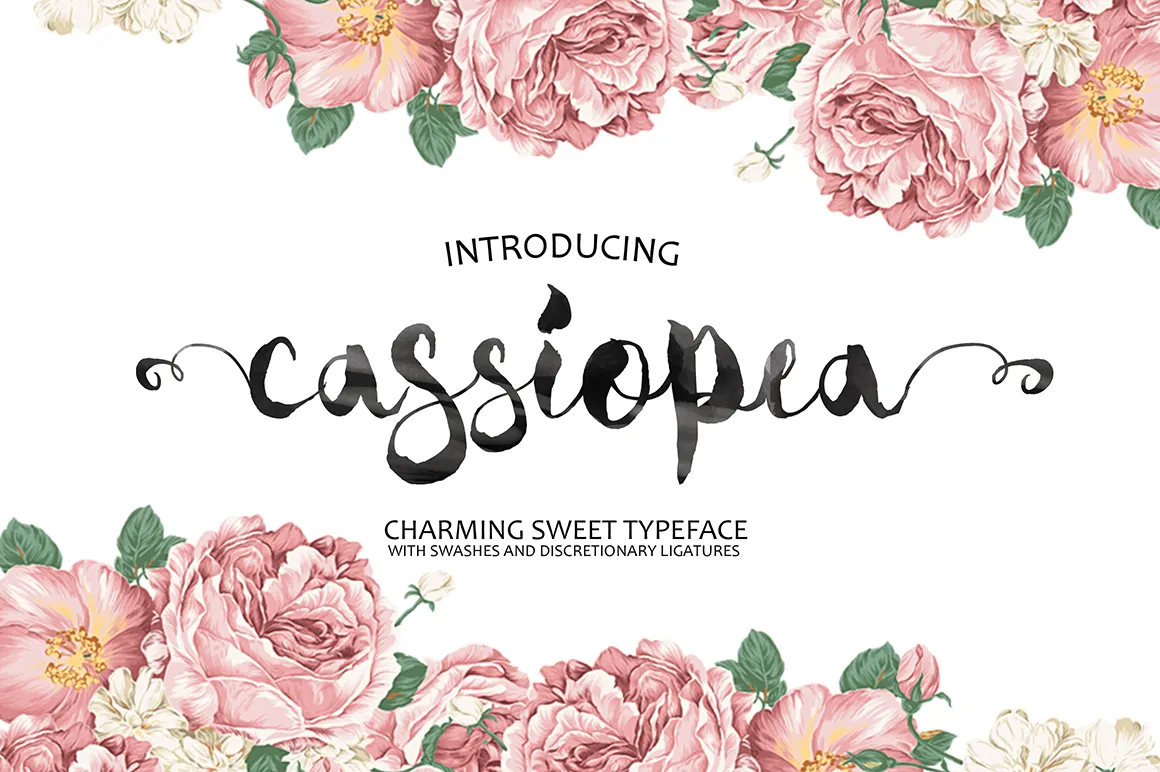
Cassiopea Brush Font – Download Grátis
A Cassiopeia Brush é uma fonte premium agora disponível gratuitamente no site The Hungry Jpeg, entre 43 fonts livres que compartilhamos lá. Estas fontes são ideais para designers e criativos que procuram um touch de luxo com um toque de elegância. Essa fonte foi projetada pelo designer Hamilton, e está disponível gratuitamente por apenas 14 dias para download. A Cassiopeia Brush é perfeita para adicionar um charme especial a qualquer projeto gráfico – seja em letras grandes no cabeçalho ou em subtítulos interessantes. Se você está procurando por uma fonte que vai dar seu trabalho de design um toque único, vale muito a pena explorar essa fonte gratuita e única. Não deixe esses dias especiais passarem sem aproveitar a oportunidade de ter esta fonte em sua coleção personalizada.